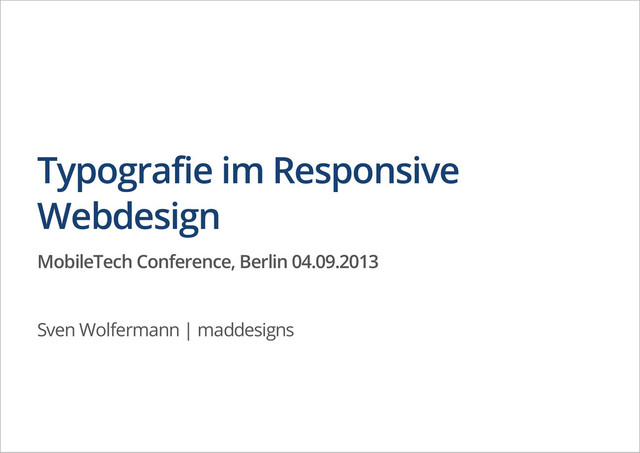
Typografie im Responsive Webdesign
Ein großer Bestandteil von Webseiten ist nach wie vor Text. Die weitreichende Unterstützung von Webfonts in modernen Browsern gibt uns die Möglichkeit, Schriftarten unserer Wahl für die Auszeichnung von Text zu nutzen. Allerdings gibt es auch Fallen bei der Verwendung von Webfonts, die gerade auf mobilen Geräten auftreten können. Lösungswege und Tipps für die Verwendung von Schrift im Responsive Webdesign. Zudem zeigt der Vortrag neue Möglichkeiten in CSS3.
2. Responsive Webdesign Flexible Spaltenraster, die auf Prozentwerte basieren Variable Bilder-
und Videogrößen – Bilder passen sich den Spalten an CSS3 um Gerätegröße abzufragen und Inhalte anzupassen · · · Quelle Bild: http://macrojuice.com/ /
3. The responsive web will be 99.9% typography — James Young
(@welcomebrand) “ ” The responsive web will be 99.9% typography /
4. Typography in ten minutes Wichtigste Fakten Bodytext gut aussehen lassen,
dann um den Rest kümmern Bodytext Schriftgröße: 15–25 Pixel Zeilenhöhe sollte bei 120–145% liegen Zeilenlänge sollte zwischen 45–90 Zeichen pro Zeile betragen Nach Möglichkeit keine Systemfont verwenden, sondern eine professionelle Webfont · · · · · /
5. Anything from 45 to 75 characters is widely regarded as
a satisfactory length of line for a single-column page set in a serifed text face in a text size […] (counting both letters and spaces) […]. —2.1.2 Choose a comfortable measure “ ” The Elements of Typographic Style Applied to the Web /
6. optimal Zeilenlänge 45 - 75 Zeichen Trent Walton nutzt einen
einfachen Trick mit * Sternchen Lorem ipsum dolor sit amet, consectetur adip*isicing elit, sed do eiusmod *tempor incididunt ut labore et dolore magna aliqua. „Wenn die zwei Sternchen in einer Textzeile sind, ist es Zeit die Schriftgröße zu erhöhen.“ Fluid Type /
7. Leseabstand zum Bildschirm The reference pixel is the visual angle
of one pixel on a device with a pixel density of 96dpi and a distance from the reader of an arm's length. For a nominal arm's length of 28 inches, the visual angle is therefore about 0.0213 degrees. For reading at arm's length, 1px thus corresponds to about 0.26 mm (1/96 inch). “ ” http://www.w3.org/TR/css3-values/#lengths /
8. Typographic scale Schriftgrößen-Empfehlung von Marko Dugonjić kurze Leseentfernung: 16px, 18px,
21px, 24px mittlere Leseentfernung: 18px, 21px, 24px, 36px lange Leseentfernung: 21px, 24px, 36px, 48px · · · Responsive Web Typography /
9. relative Schriftgröße – em CSS Anweisungen bisher b o d
y { f o n t - s i z e : 1 0 0 % ; / * d e f a u l t = 1 6 p x * / } b o d y { f o n t - s i z e : 6 2 . 5 % ; / * c a l c u l a t e f r o m 1 0 p x * / } h 1 { f o n t - s i z e : 2 . 4 e m ; / * 2 4 p x * / } p { f o n t - s i z e : 1 . 4 e m ; / * 1 4 p x * / } /
10. relative Schriftgröße – em < h 1 > Ü b
e r s c h r i f t < s p a n > d i e n o c h e i n e S u b l i n e h a t < / s p a n > < / h 1 > b o d y { f o n t - s i z e : 1 0 0 % ; } / * 1 6 p x * / h 1 { f o n t - s i z e : 1 . 5 e m ; / * 2 4 p x / 1 6 p x * / l i n e - h e i g h t : 1 ; } s p a n { f o n t - s i z e : 1 e m ; / * 1 6 p x / 1 6 p x * / d i s p l a y : b l o c k ; } Überschrift die noch eine Subline hat /
11. relative Schriftgröße – em Bei der Berechnung von em-basierenden Schriften
acht geben. Der em- Wert von font-size bezieht sich auf das Elternelement, em-Wert von margin/padding auf die eigene font-size s p a n { f o n t - s i z e : 0 . 6 6 6 6 6 6 6 6 7 e m ; / * 1 6 p x / 2 4 p x * / } Überschrift die noch eine Subline hat In fast allen Browsern ist 16px die Default-Schriftgröße, allerdings haben einige Mobile-Browser höhere Schriftgrößen. Blackberry OS 6.0 = 22px, Kindle Touch = 26px, UC-Browser = 19px. /
12. Vorteil für Responsive Webdesign b o d y { f
o n t - s i z e : 1 e m ; } @ m e d i a o n l y s c r e e n a n d ( m i n - w i d t h : 6 0 0 p x ) { b o d y { f o n t - s i z e : 1 . 5 e m ; } } @ m e d i a o n l y s c r e e n a n d ( m i n - w i d t h : 7 5 0 p x ) { b o d y { f o n t - s i z e : 2 e m ; } } @ m e d i a o n l y s c r e e n a n d ( m i n - w i d t h : 1 0 0 0 p x ) { b o d y { f o n t - s i z e : 2 . 5 e m ; } } /
44. FitText Überschriften an Bildschirm anpassen < s c r i
p t s r c = " j q u e r y . f i t t e x t . j s " > < / s c r i p t > < s c r i p t > j Q u e r y ( " . r e s p o n s i v e _ h e a d l i n e " ) . f i t T e x t ( ) ; < / s c r i p t > http://fittextjs.com/ /
45. SlabText A jQuery plugin for producing big, bold & responsive
headlines http://freqdec.github.io/slabText/ /
46. Responsive Text A jQuery plugin to set font sizes responsively
http://garyhepting.com/jquery-responsive-text/ /